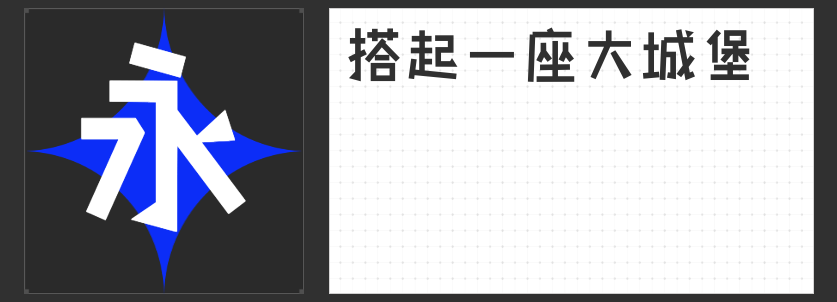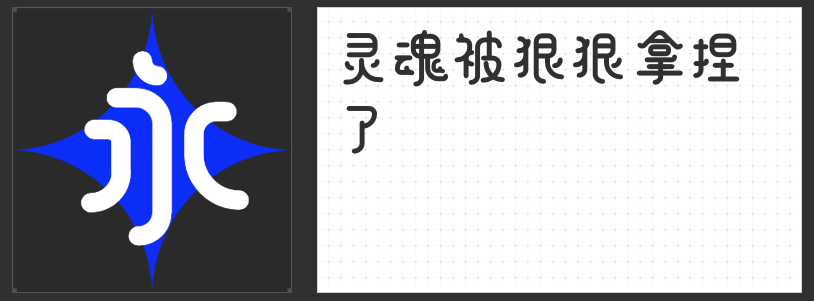
游戏视觉语言的字体革命:四款风格化字库字体赋能沉浸体验
在游戏设计的多维宇宙中,字体是构建世界观的无声叙事者。从UI界面的信息传导到角色对话的情感渲染,从技能特效的视觉冲击到场景标题的氛围营造,字体的选择直接决定玩家对虚拟世界的第一印象。本文精选四款风格迥异的商业字库字体,它们以独特的设计语言重新定义了游戏字体的美学边界。
一、字恋狂丸粒简
这款以圆角为基因的字体如同被施了软化咒语的像素块,笔画两端与转折处的0°倒角处理消解了所有锐利感,形成如棉花糖般的视觉触感。其1.5:1的宽高比设计让文字在密集排列时仍保持呼吸感,特别适合休闲游戏或儿童向产品的主菜单界面。当玩家在《动物森友会》式治愈场景中看到这种字体,潜意识中会触发安全舒适的神经反馈。
二、造字侠磅礴简繁
取法颜真卿骨法的这款字体,将书法飞白转化为数字时代的战斗痕迹。3:7的粗细对比与22°的笔锋倾斜角度,精准复现了刀剑劈砍的力学轨迹。转折处方圆结合的处理方式,既保留了篆籀的古拙气韵,又暗合现代动作游戏的打击节奏。在开放世界RPG的地图标题或技能说明中,这种字体能瞬间激活玩家的江湖代入感。
三、字恋狂灵珑简
通过模仿孩童涂鸦的"失控感",这款字体以0.8pt的笔画抖动参数构建出数字时代的手作温度。横细竖粗的非常规比例打破视觉惯性,而随机分布的圆点元素则像未擦净的蜡笔痕迹。在独立游戏或解谜冒险类作品中,这种字体能完美承载开发者对"不完美美学"的追求,让每个文字都成为叙事拼图中的特殊碎片。
四、字圈也字小积木体
以乐高积木为原型开发的这款字体,通过72°钝角与90°直角的交替使用,构建出具有三维错觉的视觉结构。其0.3mm的笔画错位设计模拟了实体积木的拼接缝隙,在科幻题材游戏的HUD界面或装备说明中,能自然唤醒玩家对机械美学的原始认知。这种字体证明:数字时代的工业感,可以通过童趣化的设计语言重新诠释。
当游戏设计师开始将字体视为可交互的视觉组件,而非静态的信息载体,这些风格化字库便成为了打开次元壁的密钥。它们用笔画重构玩法,用结构定义氛围,让每个文字都成为玩家探索虚拟世界的第一个冒险伙伴。